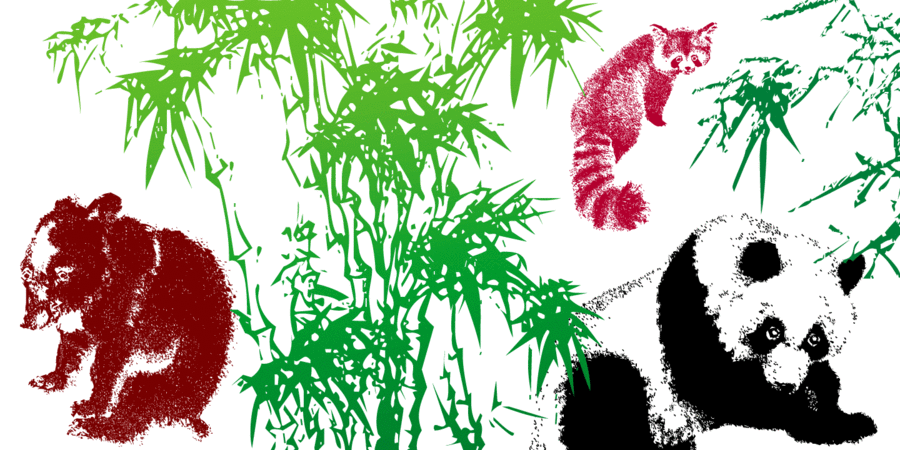
Cучасні пі-фонти – це відродження друкарської традиції політипажів на сучасному цифровому рівні. Пропонований шрифт містить понад 600 малюнків-ґліфів за мотивами культури й мистецтва Далекого Сходу та Південно-Східної Азії: краєвидів, тварин, рослин, характерних предметів та наїдків. У складі також китайські та європейські цифри різної ширини, які разом з дужками дозволяють складати числа, що нагадують печатки. Наявна певна кількість природних та штучних фактур та традиційних орнаментів, що складаються у нескінченні декоративні поверхні. Реалізовані знаки східного гороскопу, оригінально втілені триграми, наведені зразки писемностей та пам’ятки архітектури різних країн регіону. Все це сприяє універсальному використанню фонта для оформлення будь-якої продукції відповідної тематики: календарів, гороскопів, книг, часописів, путівників, меню, плакатів, текстилю, інтер’єрів тощо. Шрифт розробив Віктор Харик у 2019 році.
Функції сімейства шрифтів Yellow RiverЗастосування гарнітури у верстці:
Асоціації з сімейством шрифтів Yellow RiverОсобистість і характер гарнітури:
архаїчний, древній, племінний, культурний, художній, рукотворний, традиційний, історичний, героїчний, красивий, характерний, майстерний, прекрасний, вишуканий, ремісничий, крафтовий, казковий, рослинний, природний, живий, дерев'яний, китайський, азіатський, японський, літній, кольоровий, Східний, південний, натуральний, дикий, динамічний, апетитний, нерівний, осінній, артізанальний, екзотичний, лісовий, грунтовий
міфологія, музей, культура, мистецтво, татуювання, історія, література, епос, прикраса, ремесло, фентезі, казка, природа, тату, їжа, ресторан, обід, вечеря, інтер'єр, декор, одяг, туризм, релігія, храм, живопис, дракон, гра, карти, дерево, квіти, подарунки, тигр, меч, рамен, пельмені, хенд мейд, сад, осінь, літо, весна, паназія, риба, легенда, сувенір, пейзаж Гарнітура має ознаки стилів: